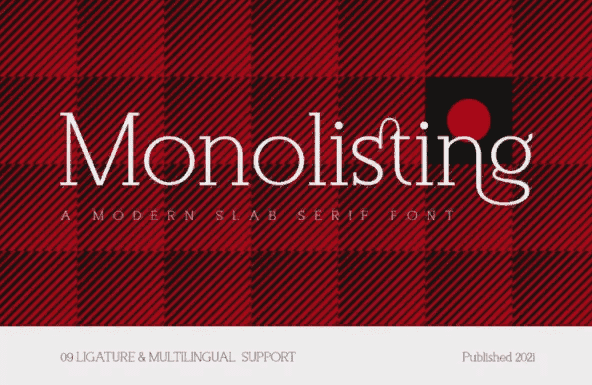
[Fontbundles] Monolisting Font (2022)
Название: Monolisting Font (2022)
[Fontbundles] Monolisting Font (2022)
Monolisting - свежий шрифт с наклонной засечкой. Его можно легко подобрать к невероятно большому набору проектов, поэтому добавьте его в свои творческие идеи и обратите внимание, как он выделяет их!